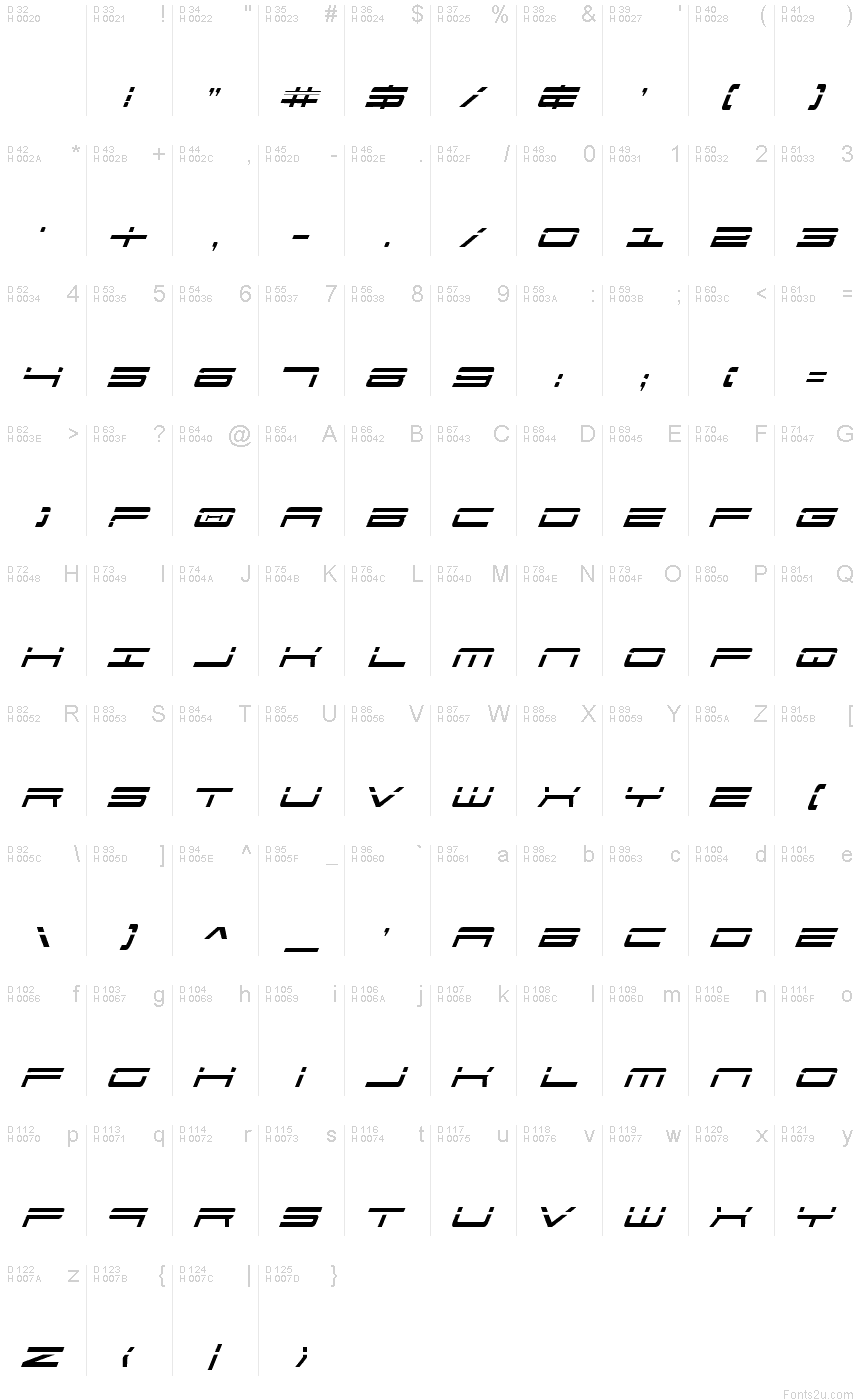
911 Porscha Laser Italic
911 Porscha Laser Italic emanuje futurystycznym stylem dzięki smukłym, szerokim literom i odważnej, laserowej estetyce. Ten krój pisma typu display, zaprojektowany przez Iconian Fonts, promieniuje poczuciem prędkości, nowoczesnej technologii i wyrafinowania. Styl kursywy dodaje całości energicznego, dynamicznego charakteru, co czyni go atrakcyjnym wyborem dla nagłówków, logotypów i przyciągających wzrok elementów graficznych. Jego unikalny, futurystyczny styl świetnie sprawdza się w wielu projektach – od brandingu inspirowanego science-fiction po zaawansowane opakowania produktów i interfejsy cyfrowe.
Poszerzona szerokość znaków potęguje wizualną siłę fontu, czyniąc go wszechstronnym narzędziem do tworzenia wyrazistych i przyciągających uwagę kompozycji typograficznych.